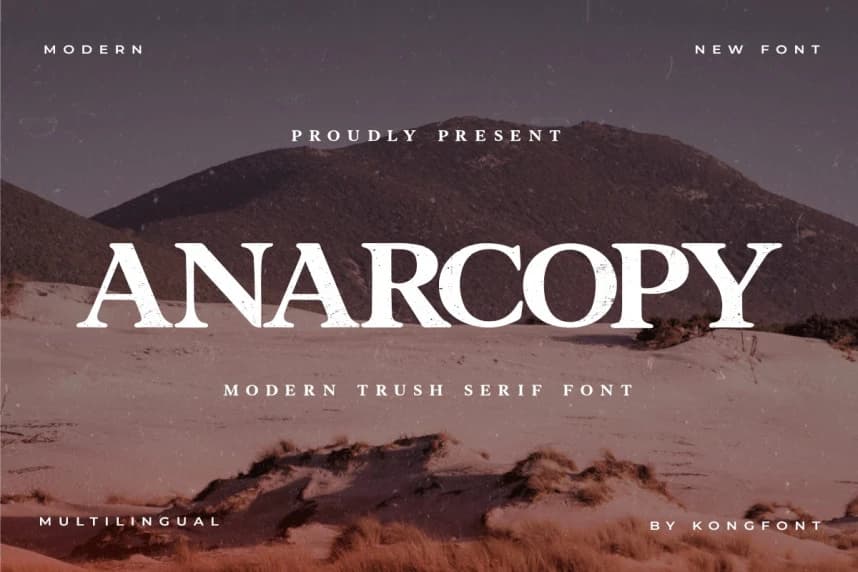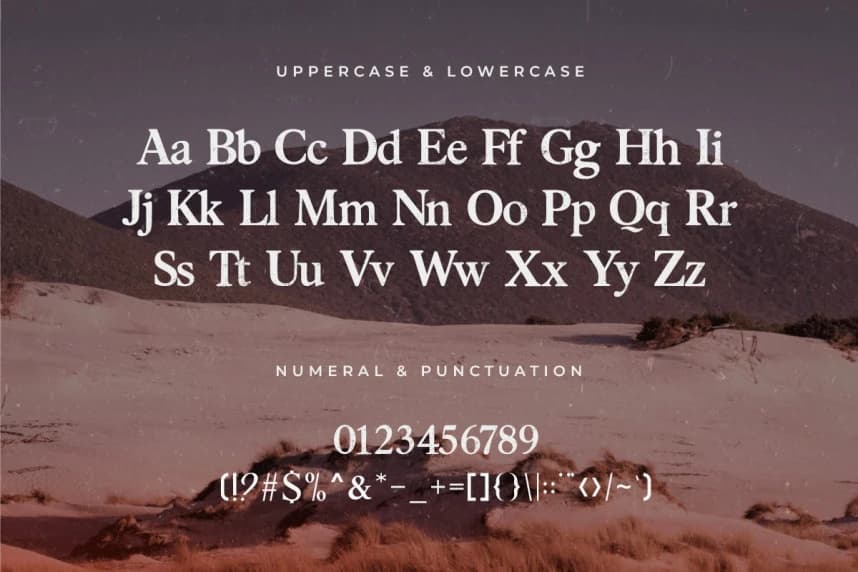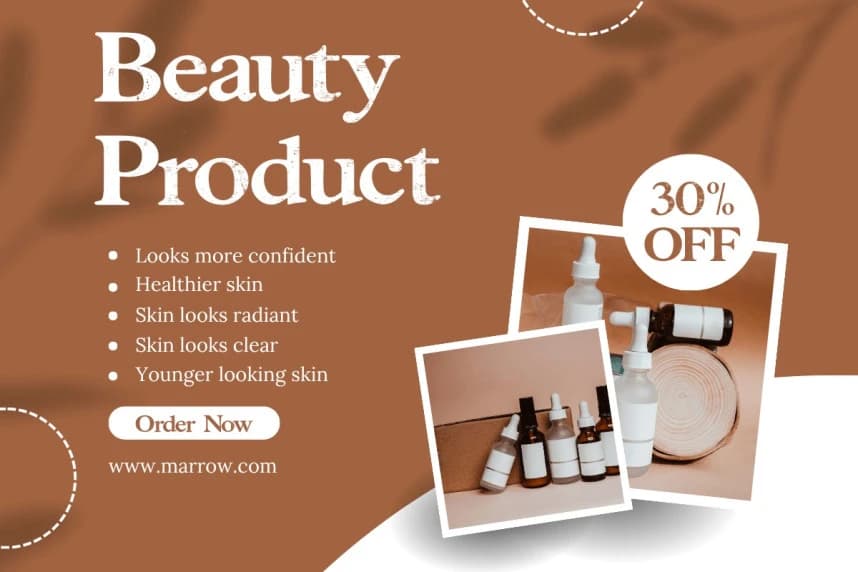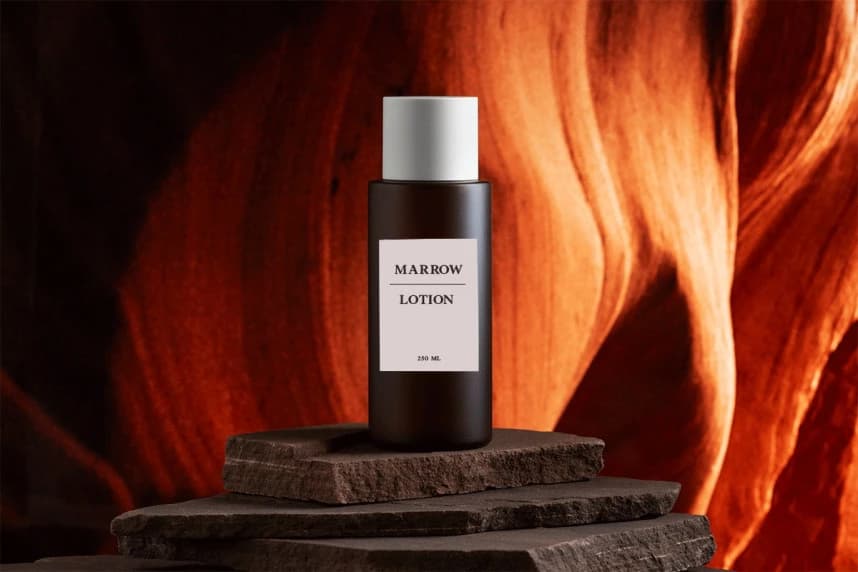
Anarcopy Font
Anarcopy Font - A Modern Classy Serif Font Bu yazı tipine verilen ad gibi, Berlin City'nin güzel bir nüansına sahip olan Anarcopy A Modern Classy Serif Font'tur. Öte yandan, Anarcopy A Modern Classy Serif Font, büyüleyici ve çağdaş harf tasarımları oluşturmanıza yardımcı olacak modern bir serif yazı
- Serif Yazı Tipi
Anarcopy Font - A Modern Classy Serif Font bu tip yazı tipinde verilen adın gösterdiği gibi Berlin City'nin güzel bir nüansına sahiptir. Öte yandan, Anarcopy A Modern Classy Serif Font modern bir serif yazı tipidir ve size çekici ve çağdaş harf tasarımları yaratmanıza yardımcı olacaktır.